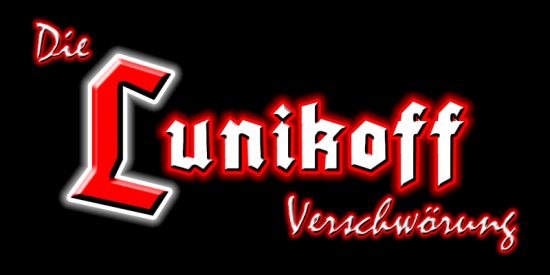
Schaftstiefelgrotesk?
Das ist jetzt zwar am momentanen Thema vorbei. Aber ich habe heute so was Schönes Im Original in den Händen gehalten, dass ich euch einen Scan davon gemacht habe: (1873)
Für die Freunde der schrägen Musik:
Hast du das? Falls ja, mit welchen Schriften wird innen gearbeitet?
Nein, hab' ich nicht. Da das ganze aber aus GB kommt, wird wohl kaum eine gebrochene Schrift verwendet werden.
Interessant ist aber das lange s im Titel.
Die verwendete Schrift auf dem Buchdeckel kennst Du dann also nicht?
Fast alle RAC-Musikgruppen (Rock Against Communism) verwende solche Schriften, auch die deutschen:
Und bei einer ganzen Reihe von CD-Heftchen sind auch die Fließtexte in Gebrochenen Schriften gesetzt.
Die Cover-Gestaltung wird oft bewußt im Stil der 20er, 30er Jahre gehalten, je nach Ausrichtung der Musikgruppe und/oder Texte kommen auch keltische Symbole mit in die Gestaltung.
Gerade wenn es aus GB kommt …
Nicht uninteressant – Camouflage im Aquarellstil, kontrastiert mit einer "bösen", schlichten Gotischen.
Innen könnte sich zumindest in den Headlines oder patternhaft, als Initial, als reine Grafik, die Titelschrift wiederholen. Mich interessiert hier einfach die Gestaltung. Kaufen werde ich mir das aber deswegen nicht …
Es gibt enge Verbindungen zwischen englischen und deutschen RAC-Gruppen - übrigens jeglichen Spektrums. Eine ganze Reihe der englischen Gruppen geben sich deutsche Namen, bei der Gestaltung zumindest einiger englischer Cover haben Deutsche aus der RAC-Szene mitgewirkt.
Mich interessiert diese Wechselwirkung bei den Designs und die Interaktion zwischen den Gruppen. Kaufen werde ich sie mir deshalb aber nicht.
Hier mal ein Beispiel für Waffenträger, die zu verspielter Fraktur gegriffen haben (photographiert auf dem Bouquinistenmarkt in Münster)
Das drückt einfach Bodenständigkeit, Gemütlichkeit, Traditionsbewusstsein aus und hat gar nicht martialisches.
Eine Vermutung am Rande: Gehen die Rap-Gebrochenen nicht irgendwie auf die Tattoo-Gebrochenen zurück? Und wo kommen die her? Knast-Tattoos? Gangsta-Image? Weiß das wer?